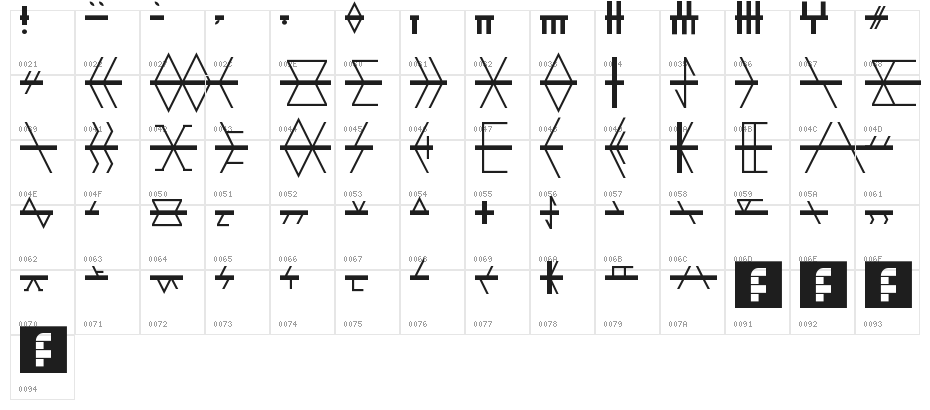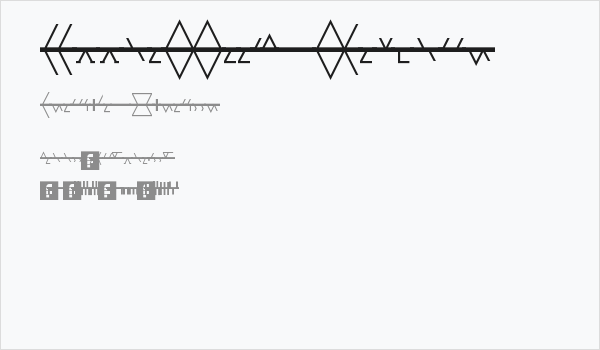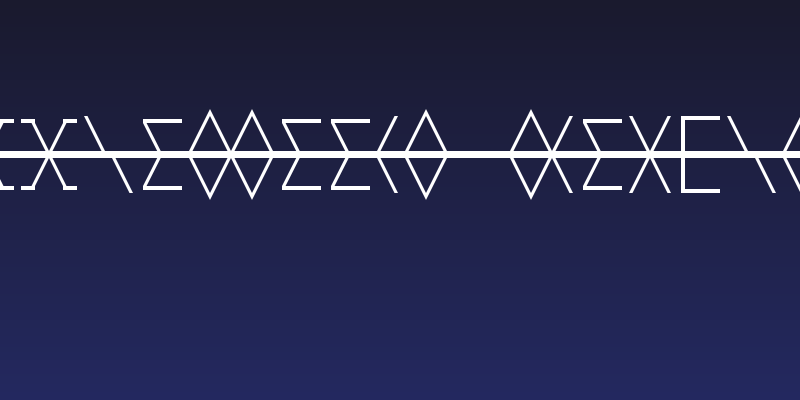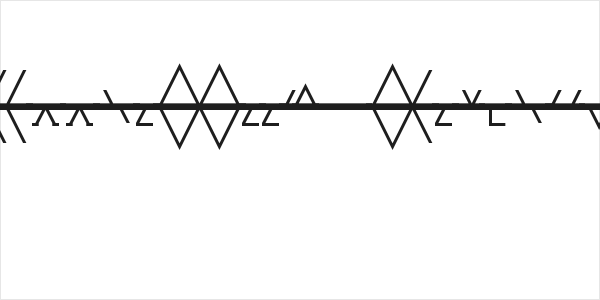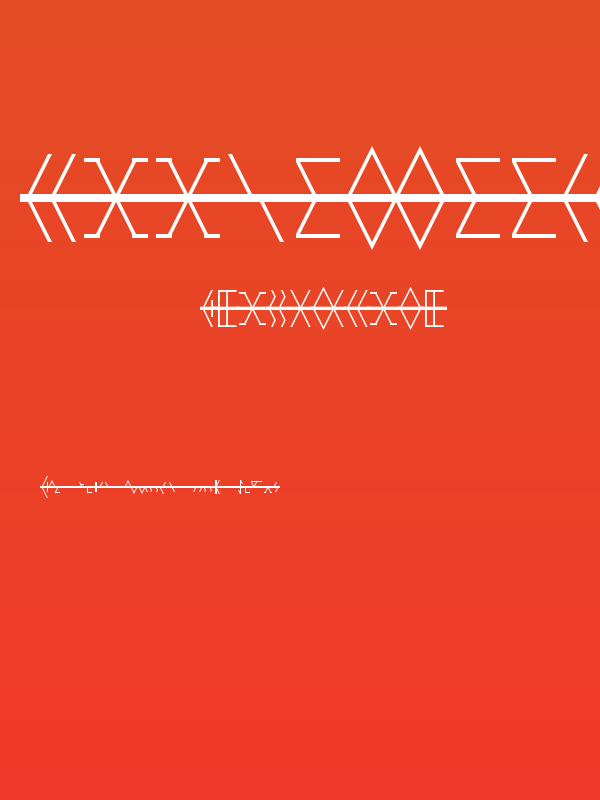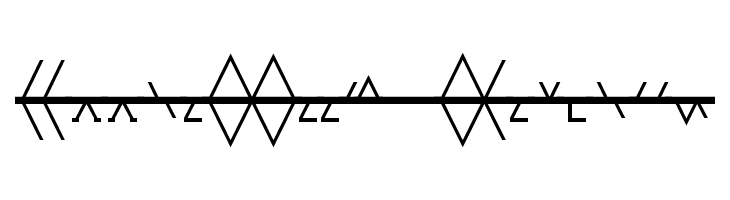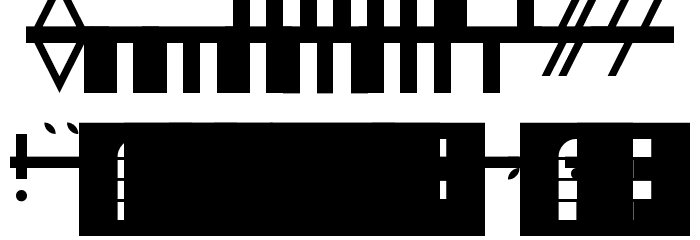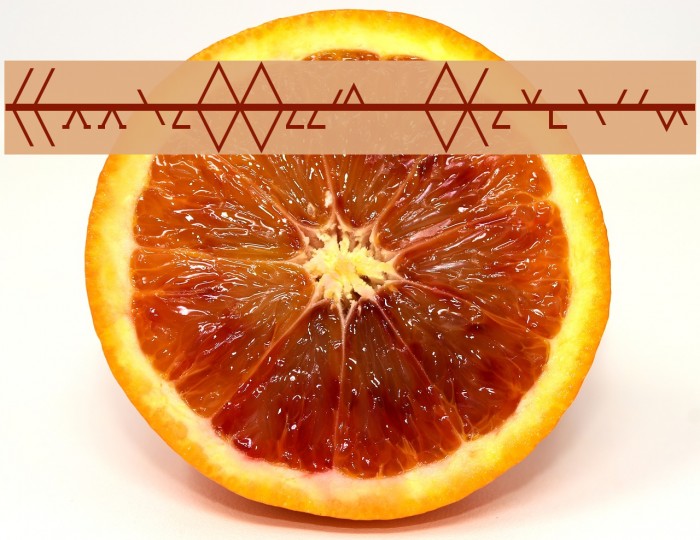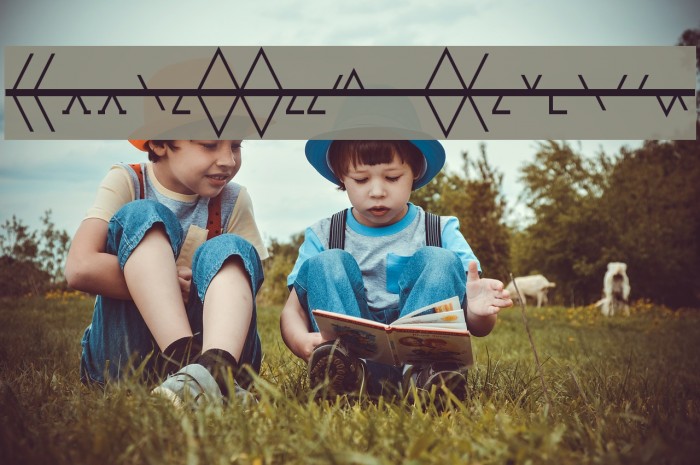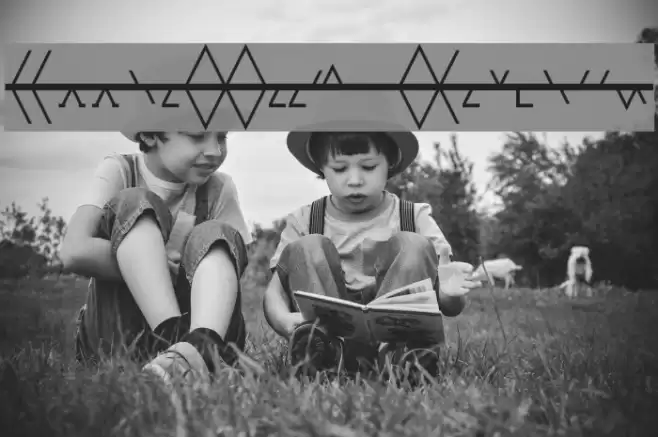
AppleBeech Regular Font
| 用途 | Logos, Titles, Artistic Projects |
| おすすめプロジェクト | Ideal for artistic projects, logos, or titles requiring a mysterious or avant-garde style. |